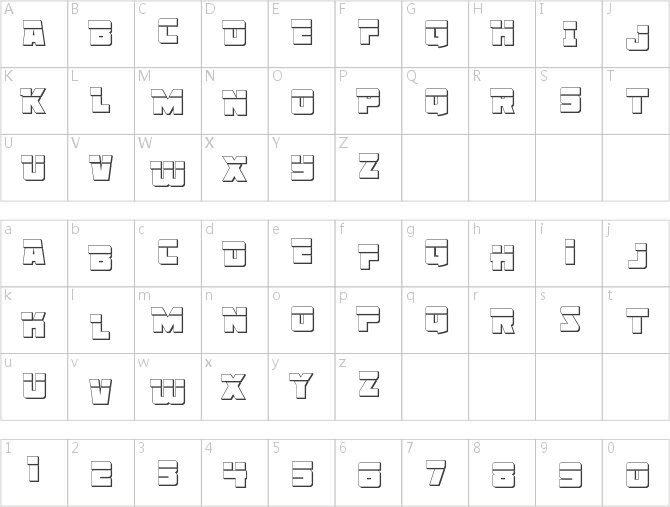
字体名称: Liberty
Liberty Legion 3D Laser
Liberty Legion 3D Laser介绍
Liberty Legion 3D Laser字体字库是一款让人赏心悦目、百看不厌的英文字体,适合各类广告和产品包装设计应用,字体大小0.04MB,格式为ttf字体,上传用户是志诚设计,作者/版权方为未知